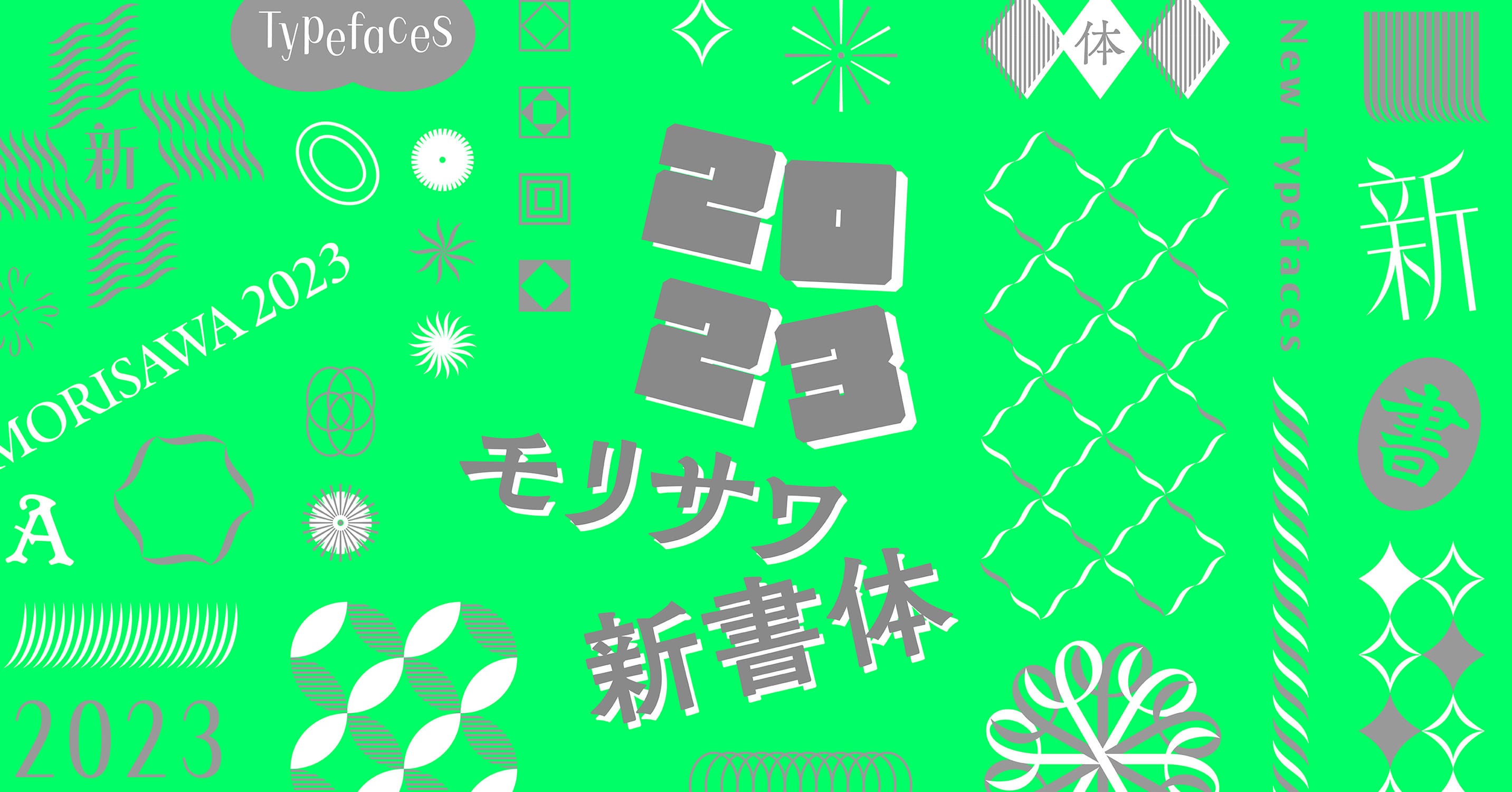
モリサワ、Morisawa Fontsの2026年度新書体を提供開始
株式会社モリサワが、フォントサブスクリプションサービス「Morisawa Fonts」にて、2026年度新書体35ファミリーの提供を開始したと発表しています。
写研創業者の石井茂吉氏のデザインをベースにした丸ゴシック体「石井丸ゴシック」や、モダンスタイルの明朝体「本蘭明朝」、伝統的な骨格ににじみやかすれを組み合わせた「淡古印」、切り絵風のデザイン書体「ソラーレ」など、写研フォント21ファミリーが追加されています。
また、新たなモリサワフォントとして、丸ゴシック体「欅丸ゴシック Oldstyle」、柔らかな角丸と長体気味のプロポーションが特徴の丸ゴシック体「ゆらら丸ゴ」、オールドスタイルのゴシック体「くらもち銘石」「くろふね銘石」、デザイン書体「タカピーク」「すすぐろ」「飛泉」、欧文書体「Othoro Pro」など12ファミリーも加わっています。
Morisawa Fontsアップグレード2026年10月版で追加された書体を紹介する図鑑仕立ての見本帳[PDF]も公開しています。
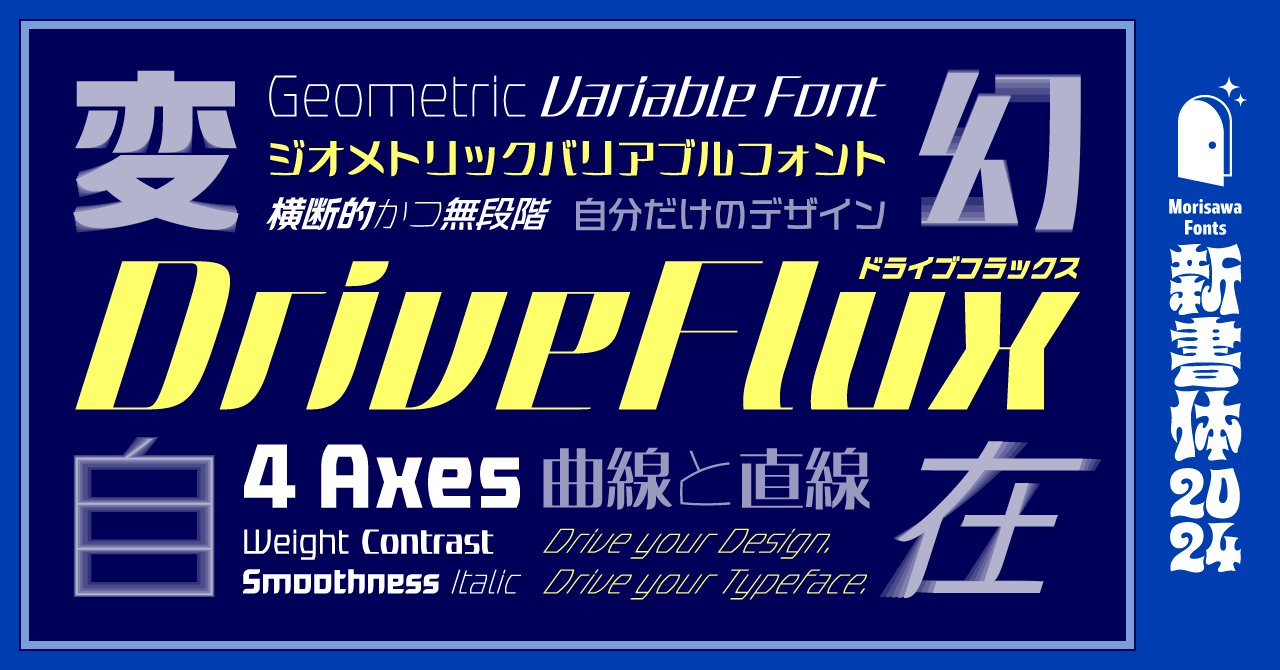
Monotype、フォントサービス「LETS」に国内書体メーカー5社の新書体を追加
Monotype株式会社が、フォントサービス「LETS」に日本の書体メーカー5社の新書体を追加すると発表しています。
新たに追加されるのは、欣喜堂、マール社、リコーPFUコンピューティング、たかデザインプロダクション、日本リテラルの5社による計484書体で、6月10日(水)より順次提供が開始される予定です。
新書体は「Monotype Fonts」でも利用できるようになります。
Morisawa Fonts、初の和文バリアブルフォントなどを提供開始
株式会社モリサワが、フォントサブスクリプションサービス「Morisawa Fonts」にて、2024年度新書体第2弾の提供を開始したと発表しています。
第2弾は、ウェイト(太さ)、スムースネス(カーブ)、コントラスト(横画の太さ)、イタリック(傾斜角)を調節できるモリサワ初の和文バリアブルフォント「DriveFlux」や、ハングルのUDフォント「Clarimo UD KR」、インドと東南アジアの文字に対応した「Role Sans」シリーズ、Occupant Fontsの欧文書体「Magmatic」「Eggwhite」「Dispatch 2」など合計37ファミリーです。
モトヤ LETSなどにデザイン書体「モトヤクレイル 2」が追加
フォントワークス株式会社が、年間定額制フォントサービス「モトヤLETS」「学生向けモトヤLETS」、ウェブフォントサービス「FONTPLUS」にて、デザイン書体「モトヤクレイル 2」の提供を開始したと発表しています。
モトヤクレイル 2は、文章に「ツヤ」「光沢感」を付与できるデザイン書体で、フランス語で「明るい」「光」を意味する「Clair」(クレイル)と名付けられています。
モリサワ、「Morisawa Fonts」「MORISAWA PASSPORT」で新書体を提供開始
株式会社モリサワが、フォントサブスクリプションサービス「Morisawa Fonts」「MORISAWA PASSPORT」と 、iPadOS向けフォントアプリ「MORISAWA PASSPORT for iPad」[App Store]にて、2023年の新書体の提供を開始したと発表しています。
今回のアップデートでは、リニューアルした「A1明朝(AP版)」や「UD新ゴ コンデンス(AP版)」、個性派書体「ボルクロイド」「月下香」「アルデオ」「つぶてん」など262書体(iPad向けアプリのStandard Packは199書体)が追加されています。
Monotype LETS、「Univers」など100書体を追加
フォントワークス株式会社が、年間定額制フォントサービス「Monotype LETS」にて、991書体を追加すると発表しています。
第1弾として「Univers」「Woodford Bourne PRO」「Verbatim」の100書体が追加されており、10月には369書体、2024年2月には522書体が追加される予定です。
モリサワ、2023年度の新書体16ファミリーを発表
株式会社モリサワが、2023年秋にリリースする新書体16ファミリーを発表しています。
• ボルクロイド
字面が大きく直線のみで構成されたパワフルでエッジの効いたデザイン書体
• 月下香
ミステリアスな印象のデザイン書体
• アルデオ
幾何学的な骨格に丸みのあるエレメントを組み合わせたデザイン書体
• つぶてん
可愛らしい太ゴシック風デザイン書体
• 欅明朝 Oldstyle
• 欅角ゴシック Oldstyle
金属活字からインスピレーションを受けたオールドスタイルの書体
• プフ サワー
• プフ ソワレ
レトロな雰囲気のデザイン書体
• 美風
台湾の玉川設計所が手掛ける繁体字フォントをベースにしたデザイン書体
• 翠流きら星
台湾の子会社であるArphic Typesの「AR白玉しらたま書体」の漢字を組み合わせたデザイン書体
• 翠流ゆゆポップ
太い平芯のマーカーペンで書いたようなPOP書体
• 瓦明朝
毎日新聞社が開発したモダンテイストの明朝体
• 史仙堂しせんどう楷書体
太楷書体
• Lutes UD PE Arabic
• Lutes UD PE Devanagari
• Lutes UD PE Thai
アラビア文字、デーヴァナーガリー、タイ文字のセリフ書体